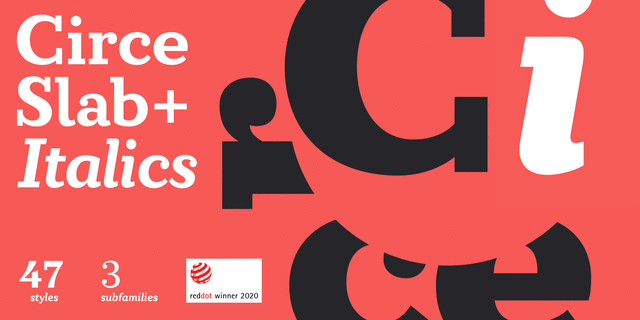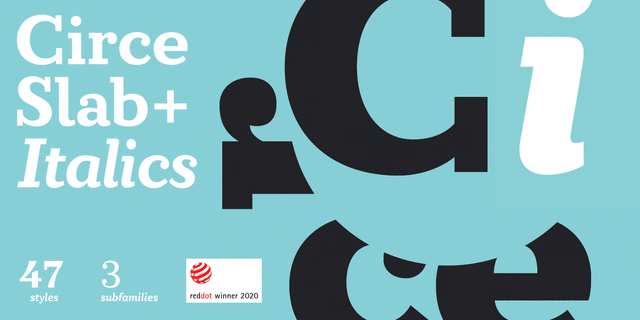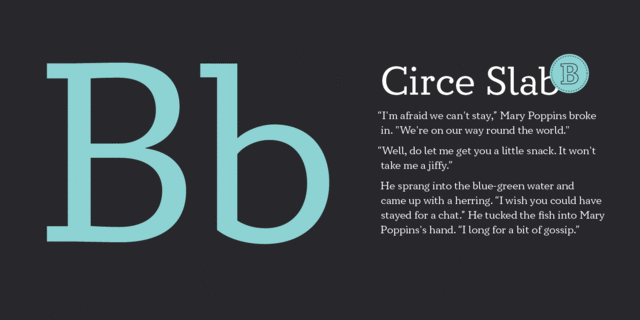
Circe Slab B — слабоконтрастная брусковая версия популярного геометрического гротеска Circe. Победитель Red Dot Award 2020 в номинации Типографика. Гарнитура содержит вариации по насыщенности и контрастности, в том числе три регулярных начертания от полностью неконтрастного геометрического (Circe Slab A) до почти антиквенного контрастного (Circe Slab C). Кроме того, все текстовые начертания имеют зауженные версии. Знаковый состав шрифта включает капитель, минускульные цифры и богатый набор альтернативных прописных и капительных знаков. Регулярные начертания Circe Slab подходят для набора длинных текстов, а самые светлые и жирные для использования в крупном кегле. 1-е место в номинации «Кириллица» на международном конкурсе Granshan 2019. Шрифт разработан Александрой Корольковой при участии Олексы Волочая и выпущен компанией Паратайп в 2018 году. Курсивные начертания были добавлены в 2021 году.
деликатный, чистый, легкий, прохладный, свежий, модный, городской, тонкий, современный, строгий, ясный, ровный, понятный, качественный, устойчивый, стабильный, статичный, культурный, гуманитарный, образованный, точный, твердый, мотивирующий, яркий, заметный, выразительный, сильный, уверенный